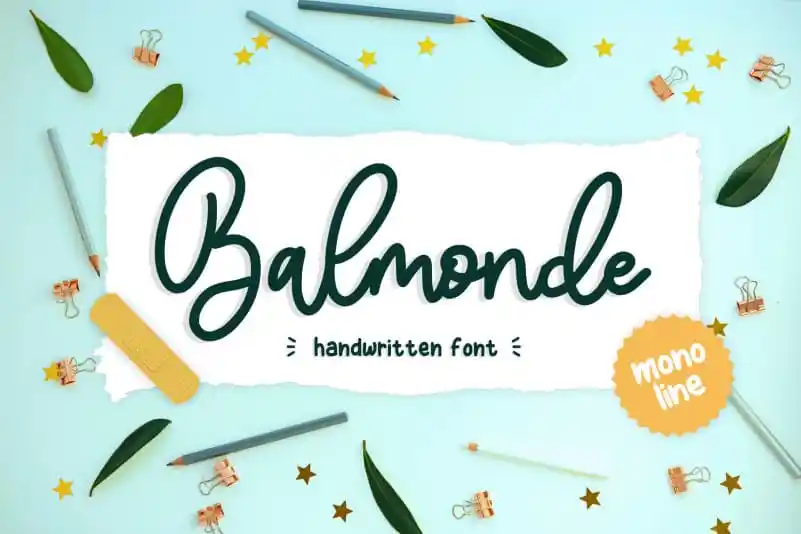
Aqui está uma descrição para a página de download da font “Balmonde Handwritten Font”, seguindo as regras solicitadas: Aqui está Balmonde, uma elegante e moderna fonte escrita a mão que combina clareza com um toque nostálgico. Ideal tanto para aplicativos gráficos profissionais quanto para projetos pessoais onde você quer destacar o texto sobre um fundo. Suas linhas fluidas e sua tipografia minimalista criam uma atmosfera de autenticidade que a torna perfeita para embelezar logomarcas, embalagens de produtos ou até mesmo textos nas redes sociais. Com suas curvas suaves e traços delicados, Balmonde oferece um toque moderno à sua tipografia. Seja ela usada em revistas, sites pessoais ou qualquer outro projeto que deseje dar um toque único, essa fonte escrita a mão será uma excelente escolha. A versatilidade desta fonte torna-a perfeita para todos aqueles que procuram algo diferente e elegante para suas necessidades de design gráfico.